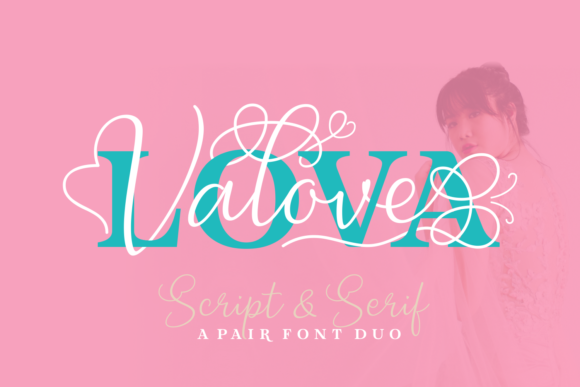
Lova Valove Font Duo – Download Grátis
A Lova Valove Font Duo é uma dupla única que inclui uma versão script elegante e outra versão serif marcante criada por Situjuh. Esta combinação inovadora de estilos traz um toque romântico com oswashes e corações, enquanto a versão serif adiciona força e destaque aos seus projetos. É perfeitamente compatível tanto para uso independente quanto em conjunto, garantindo que qualquer projeto seja destacado. Ideal para designers que buscam adicionar uma personalidade única a suas criações, esta fonte é uma escolha ótima para quem deseja incorporar sofisticação e modernidade em seus trabalhos visuais.